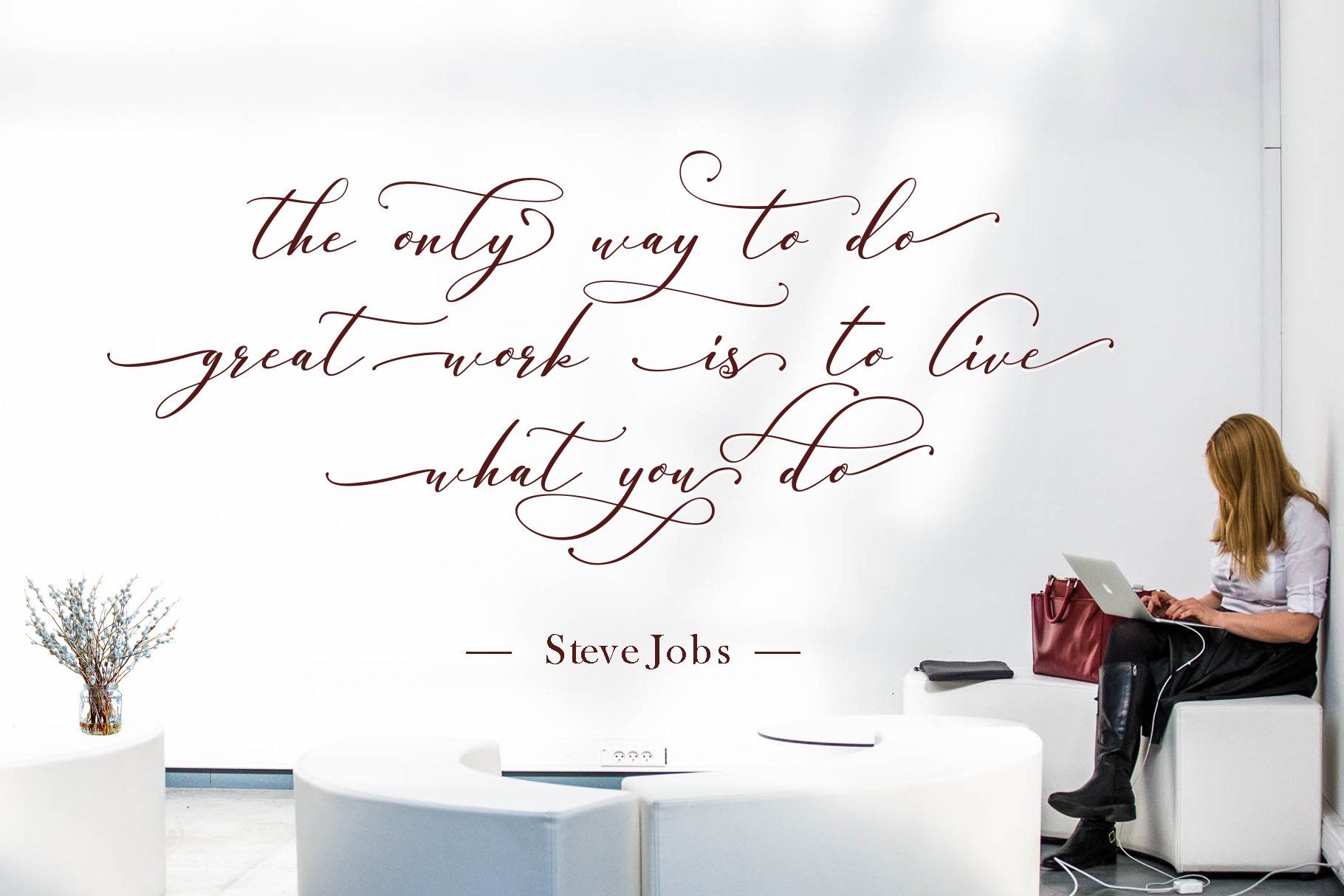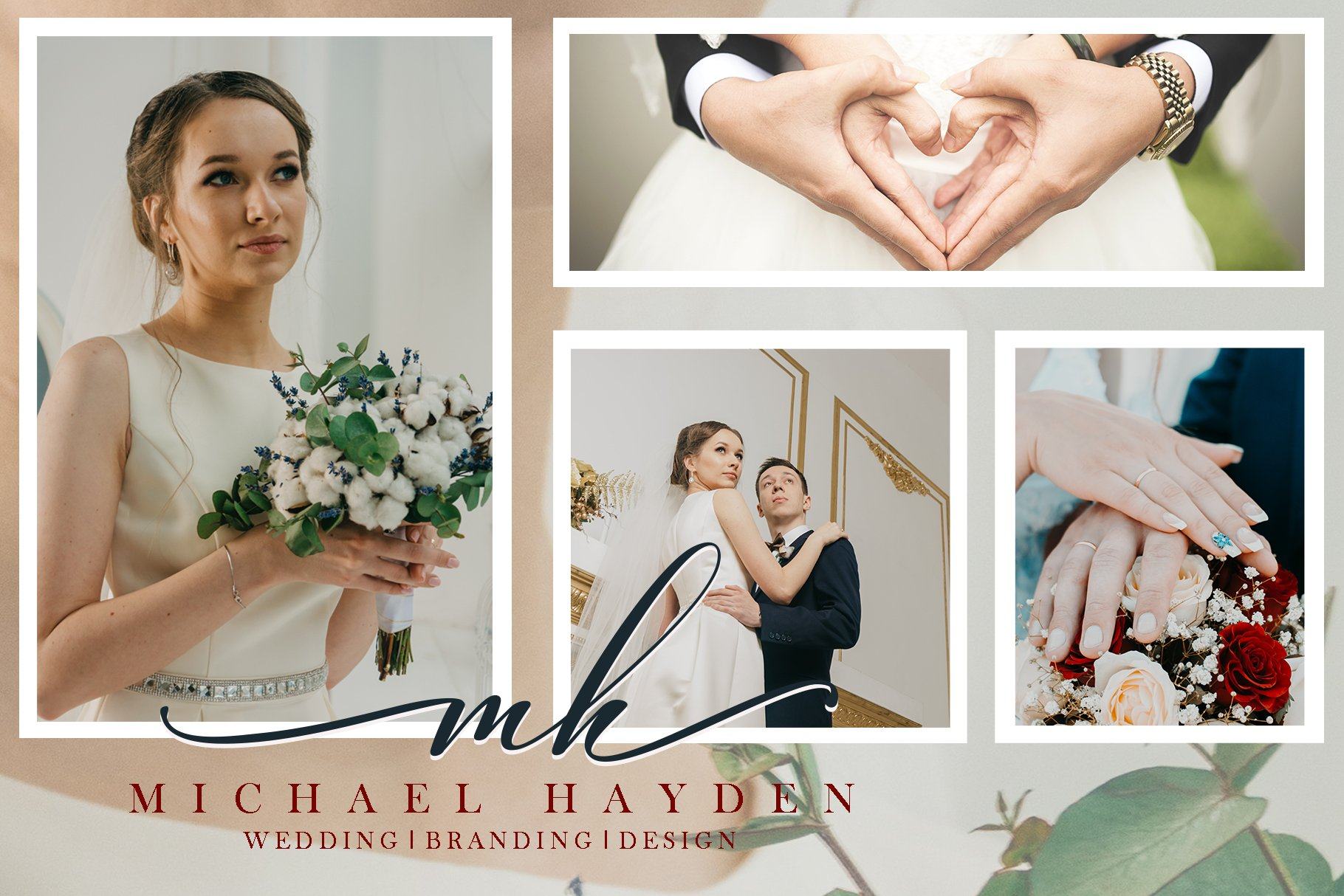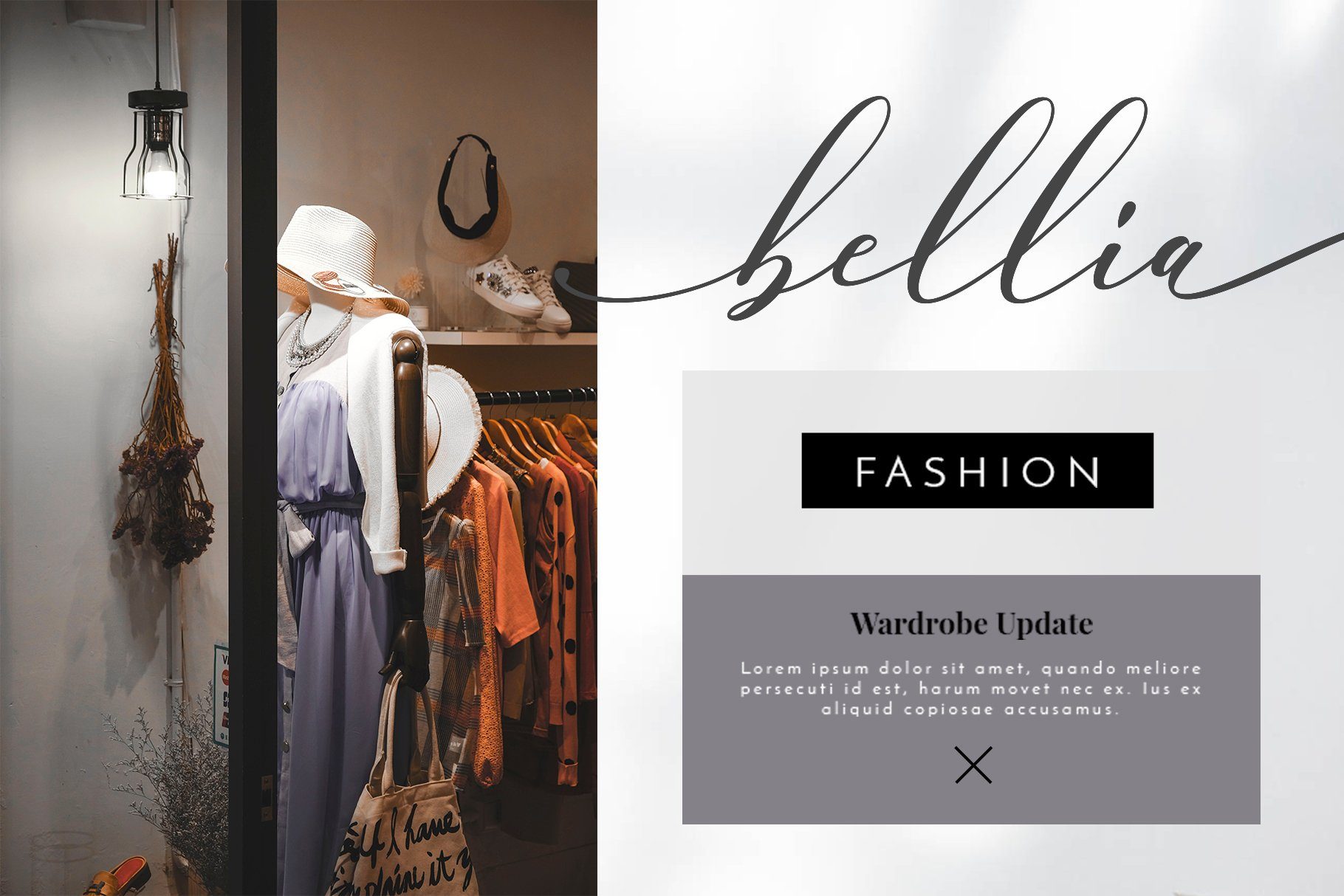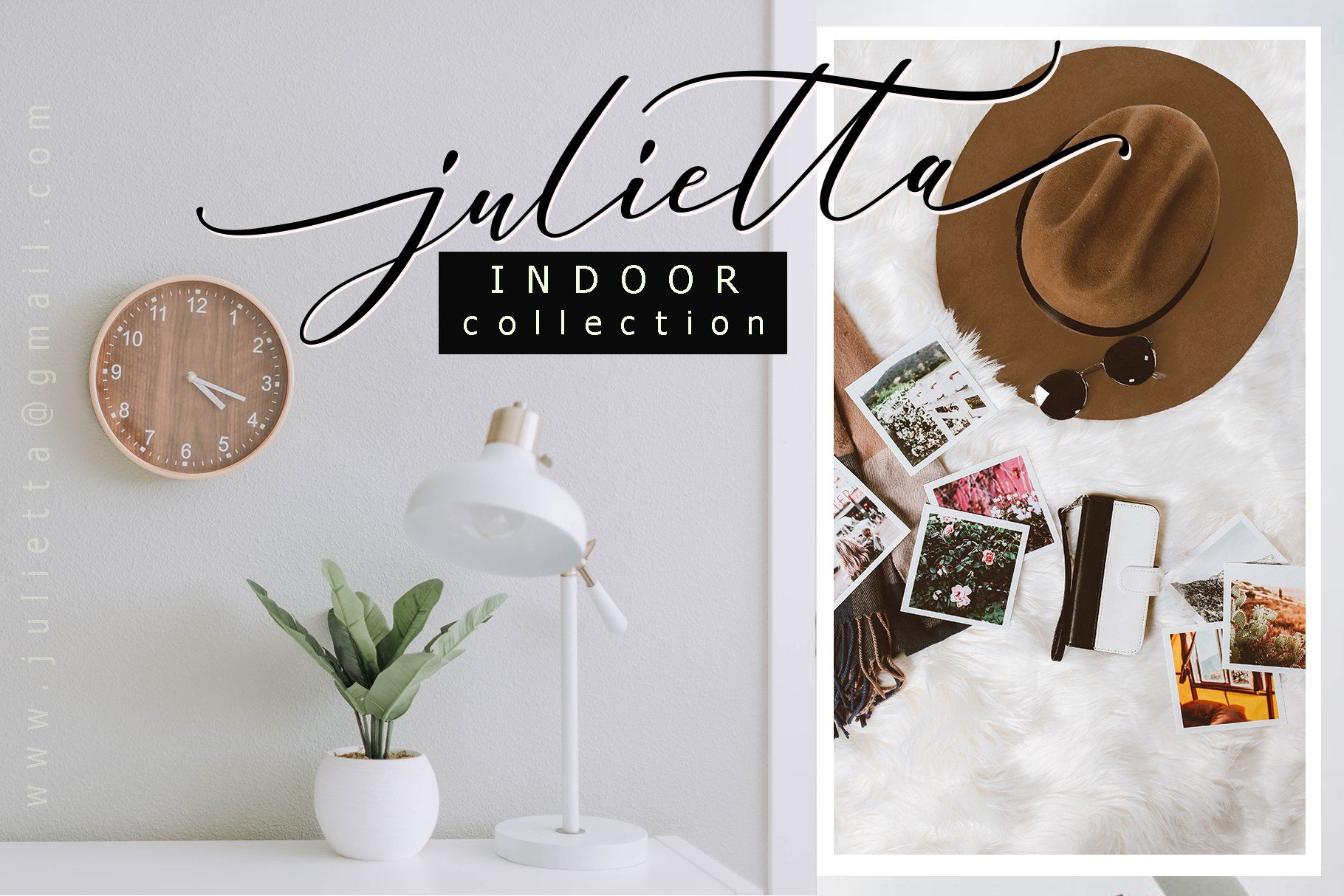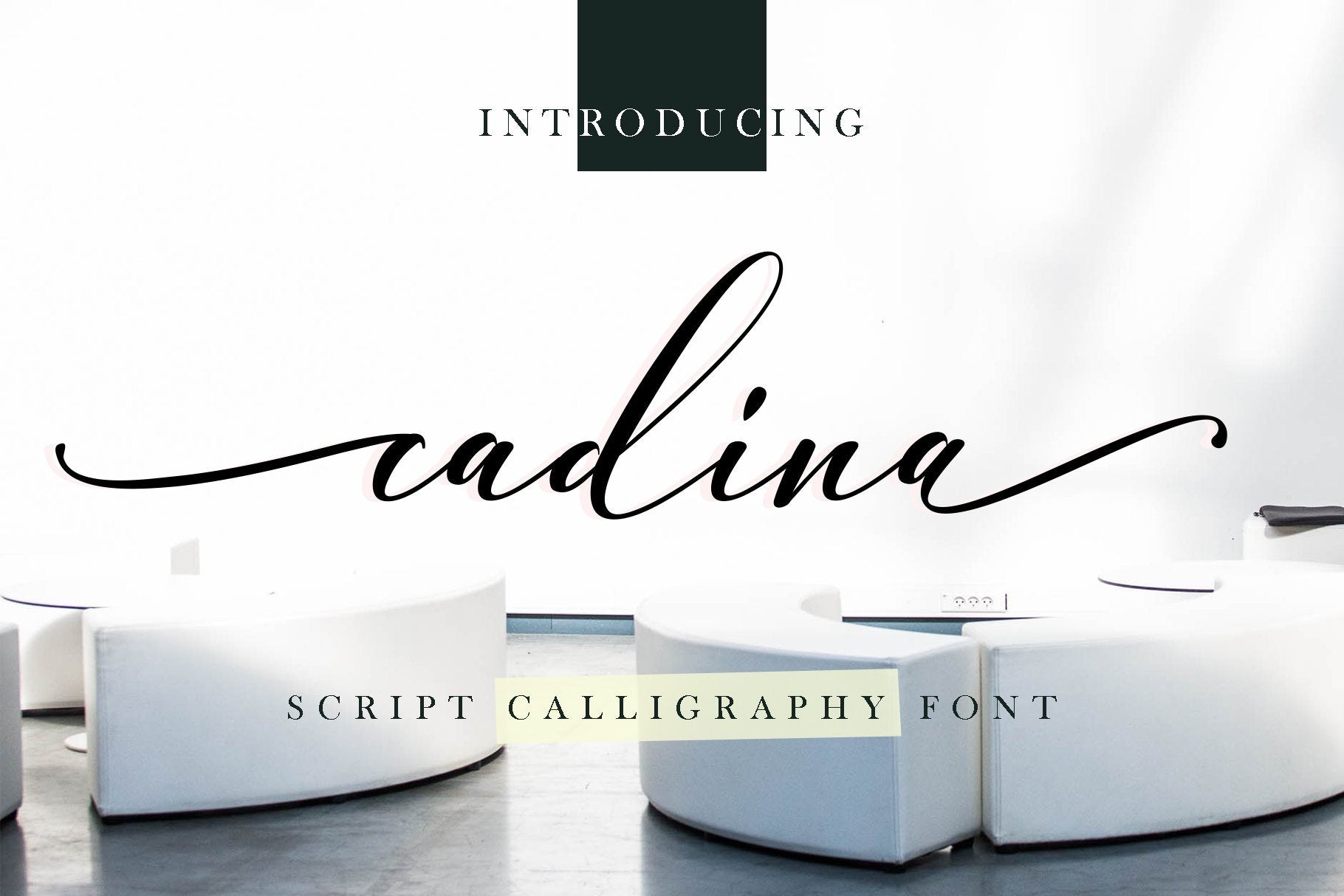
About cadina script calligraphy
Memperkenalkan kaligrafi Skrip cadina font baru yang elegan! Font ini khusus dibuat untuk Anda yang membutuhkan sentuhan elegan untuk mendesain proyek Anda selanjutnya dengan hasil yang sempurna dan menakjubkan. cadina Script A very beautiful and interesting script, and comes with a perfect line for use for various purposes. Like titles, signatures, logos, correspondence, wedding invitations, letterheads, nameplate, labels, bulletins, posters, badges, Branding, Greeting Cards, etc. cadina Script is built with OpenType features and includes start and end. It comes with OpenType Stylistice set, Initial, swashes, ligatures and everything to add a touch to your design and also supports other languages 🙂 What’s Included cadina OTF cadina TTF